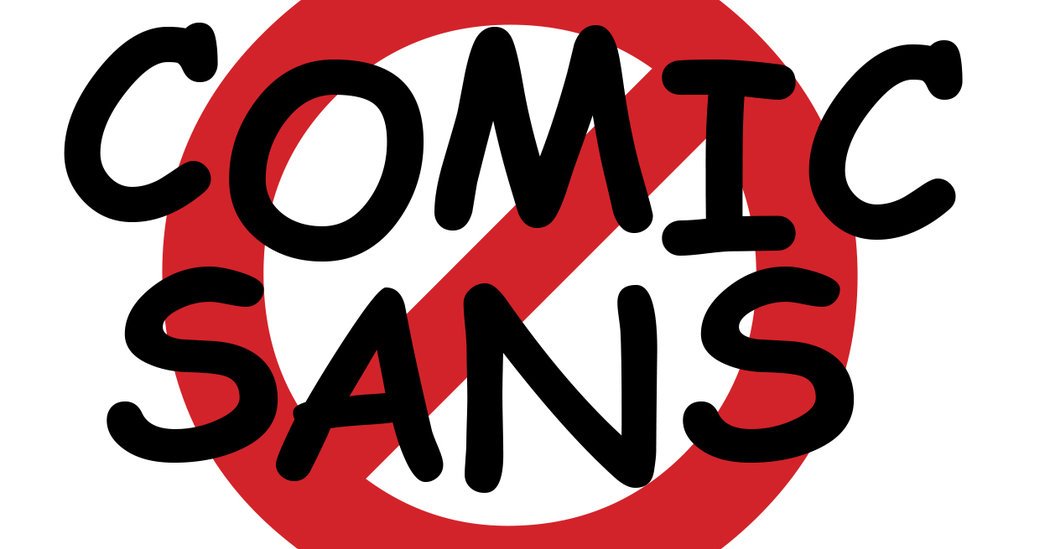
C’è stato un tempo in cui ogni grafico, allora bambino, passava le ore a scegliere il font perfetto su una pagina vuota di word. È già da allora che è iniziata l’ossessione per il font più amato e quello più odiato. Potremmo dire che è una cosa soggettiva, e la maggior parte delle volte lo è, ma ci sono alcuni font che proprio non si riescono a farsi amare da nessuno, o quasi. Quali sono i font che nel tempo sono stati letteralmente bannati dalla maggior parte dei designer?
#WorstFontEver
Ditemi perché odiate quel font! Tempo fa sui social apparve l’hashtag #WorstFontEver, il peggior font di sempre. Il primato, tra l’altro è già stato ottenuto da tempo, è il comic sans il font più odiato da grafici e designer di tutto il mondo. Ma perché è stato deciso all’unanimità di bannarlo?
Ma la sfida lanciata da Creative Market, la pagina che ha diffuso l’hashtag, è molto più ampia, vuole raccogliere tutti i font più odiati che negli anni sono stati bannati dai designer, nonché le motivazioni che hanno portato a questa decisione. Appare così la prima lista dei font più odiati e sono undici.
Comic Sans
“Rovina le presentazioni in Power Point dal 1994”
Molto esaustiva la descrizione fornita da uno dei tanti sostenitori contro il comic sans. Ma perché questo font è così odiato?
Il comic sans è nato nel 1994, appunto, dalla mano di Vincente Connare, creatore tipografico della Microsoft Corporation. Il font è nato per diventare uno dei font standard di Microsoft Word. E così è stato, si è subito diffuso moltissimo, ma allo stesso tempo è iniziato l’odio dei designer di tutto il mondo.
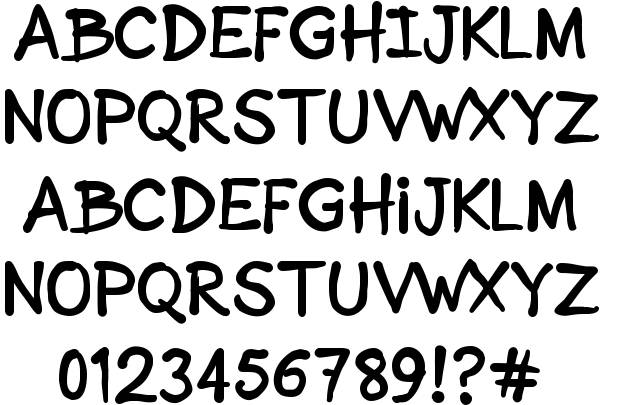
Oggi esso rappresenta “tutto ciò che di antiquato, infantile e poco professionale si possa trovare in rete”.
Nessuna parola dolce, quindi, per quel font tanto odiato, che è stato creato con tanto amore. Connare, infatti, racconta che voleva creare un font che ricordasse lo stile dei fumetti. A quel tempo stava seguendo delle graphic novel, quali Watchmen e il Cavaliere Oscuro. Così inizio a tracciare la sua idea con il mouse, non doveva essere qualcosa di perfetto, ma “volutamente sbagliato”, delle linee imperfette.
Ma il suo autore non accetta volentieri le critiche. Infatti spesso ci tiene a sottolineare che Comic Sans “era fatto per gli utenti inesperti di computer, e in quel campo è riuscito nel suo scopo”.
I font bannati dai designer
Ecco, gli altri font bannati dai designer, quelli più odiati di sempre secondo la lista del #WorstFontEver, dopo Comic Sans:
- Trajan “Il font usato in ogni genere di locandina cinematografia, a prescindere dal genere e dal periodo di tempo”;
- Bleeding Cowboys “Campione mondiale di illeggibilità nell’ambito delle copertine degli album e dei pessimi tatuaggi”;
- Lobster “Lo script dallo stile retrò cui nessun designer amatoriale può assolutamente resistere”;
- Papyrus “Quel look egiziano è così alla moda in questo momento!”;
- Zapfino “Il carattere che Zorro userebbe per i suoi inviti di nozze”;
- Bank Gothic “Solo un altro carattere per le locandine cinematografiche”;
- Helvetica “L’ubiquità genera disprezzo”;
- Hobo “Quelli di Hazzard hanno chiamato, rivogliono il loro carattere indietro”;
- Times New Roman “Nulla dice “Compiti del liceo inglese” meglio del Times New Roman”;
- Arial “Il cugino brutto e strano dell’Helvetica”.